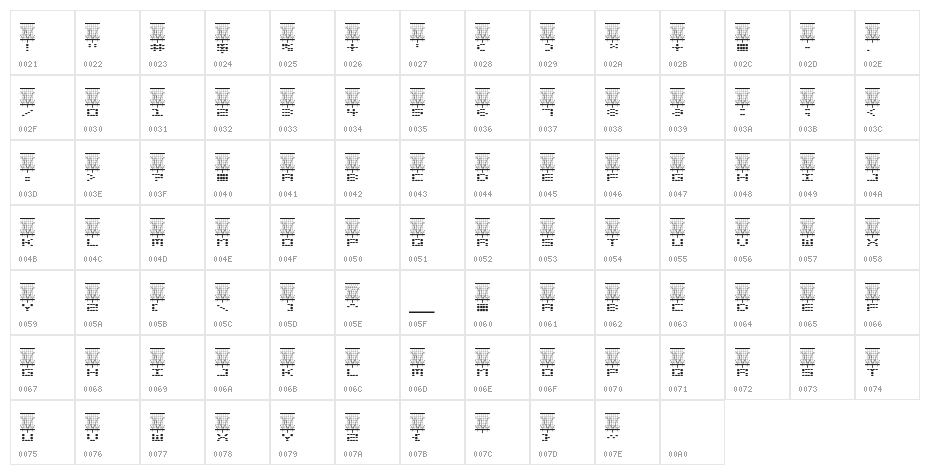
Stereo Lab Font
| Caso d'uso | Logos, Headlines, Digital Art |
| Progetti proposti | Ideal for retro-themed designs, tech-inspired branding, digital art projects, and any creative work that seeks to evoke nostalgia for early computing and digital displays. |